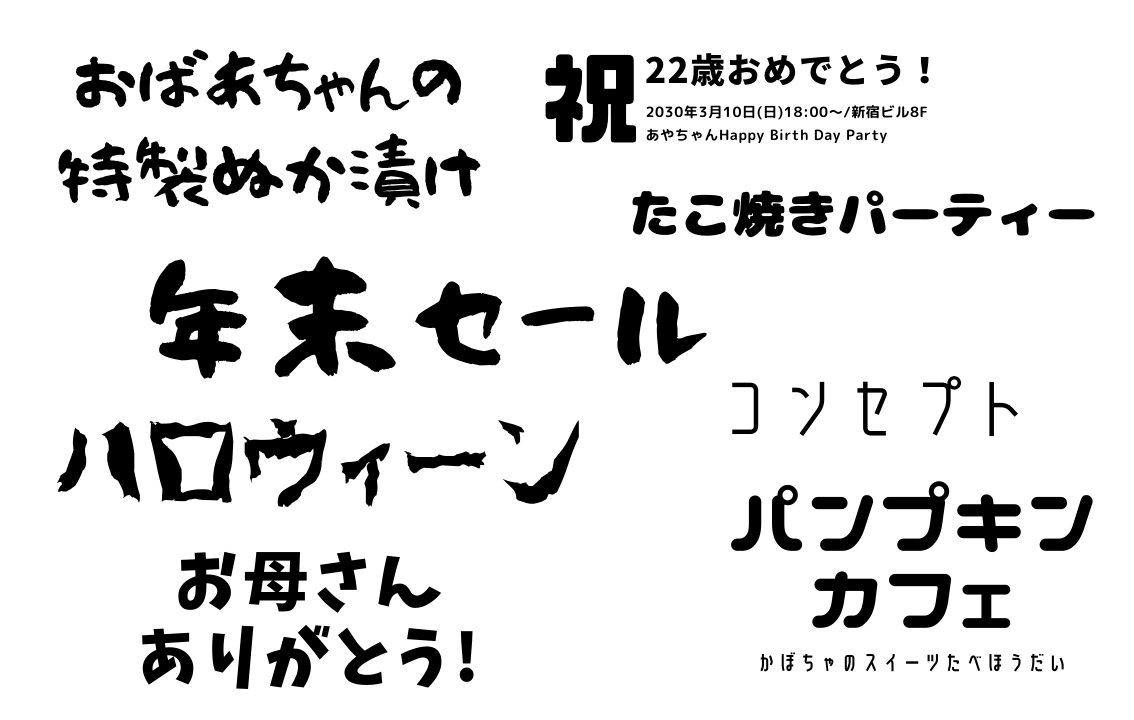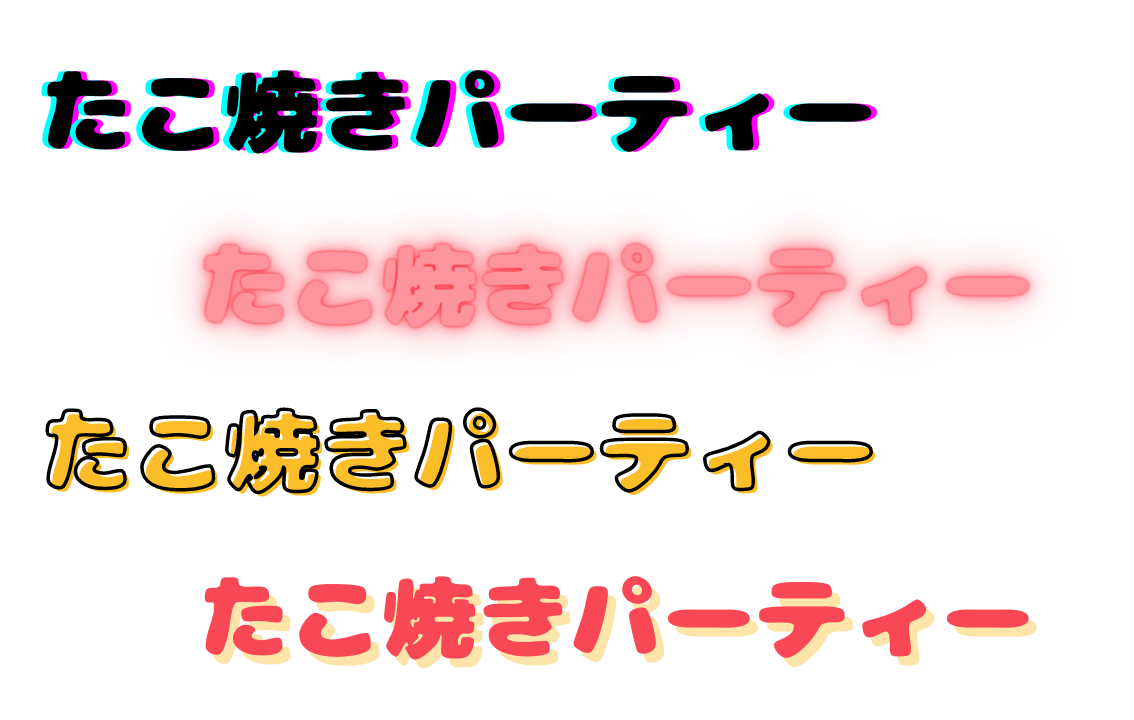
日本語フリーフォント
何百種類もの日本語フリーフォントをご用意しています
Canvaでは、何百種類もの日本語フリーフォントをご用意しています。かわいいフォント、手書き風のフォント、定番のフォント、ポップなフォント、高級感のあるフォントなど、さまざまなフォントが揃っています。フォントを変更するときでも、フォント名と字体を見ながら作業ができるので、デザインに合ったフォントを選びやすくなっています。また、あらかじめ加工されたフォントをデザインに挿入することも可能です。
日本語フリーフォントにエフェクトを付けられます
Canvaなら、日本語フリーフォントに、さまざまなエフェクトを簡単に付けることができます。テキストを選択したら、フォントの加工メニューから加工できるようになっています。色の変更、フォントサイズの変更はもちろんのこと、縦書き、袋文字、中抜き、影付け、浮き出しなどの加工も簡単にできます。また、フォントに背景を付けたり、グリッチ加工、ネオン加工も、ワンクリックで完了。円形に沿わせて、湾曲させることも可能です。
日本語フリーフォントで、動画にテロップも入れられます
Canvaなら、日本語フリーフォントを使って、テロップも入れられます。何百種類ものフォントをご用意していますので、動画の雰囲気にぴったりのフォントがきっと見つかります。動画に文字を入れるときでも、フォント色の変更、袋文字、回転、湾曲、縦書き、行間の調整などが可能です。もちろん、ひとつのシーンで別のフォントや加工もできます。さらに、テロップにアニメーションを付けることもできるようになっています。
• はい。無料で使える日本語フォントも豊富にご用意しています。Canvaのおすすめ日本語フリーフォントや明朝体フリーフォント、数字フリーフォント、うちわ文字フォント、筆文字フォント、レトロフォント、漫画フォントをぜひご利用ください。
• テキストを選択すると、フォントを選択できるようになります。フォントリストでは、フォントの表示例を見ながら選べるようになっています。
• はい、Canvaには多言語のフォントが豊富に揃っています。Canvaのおすすめ英語筆記体フリーフォントやおすすめ韓国語フリーフォントをぜひご利用ください。